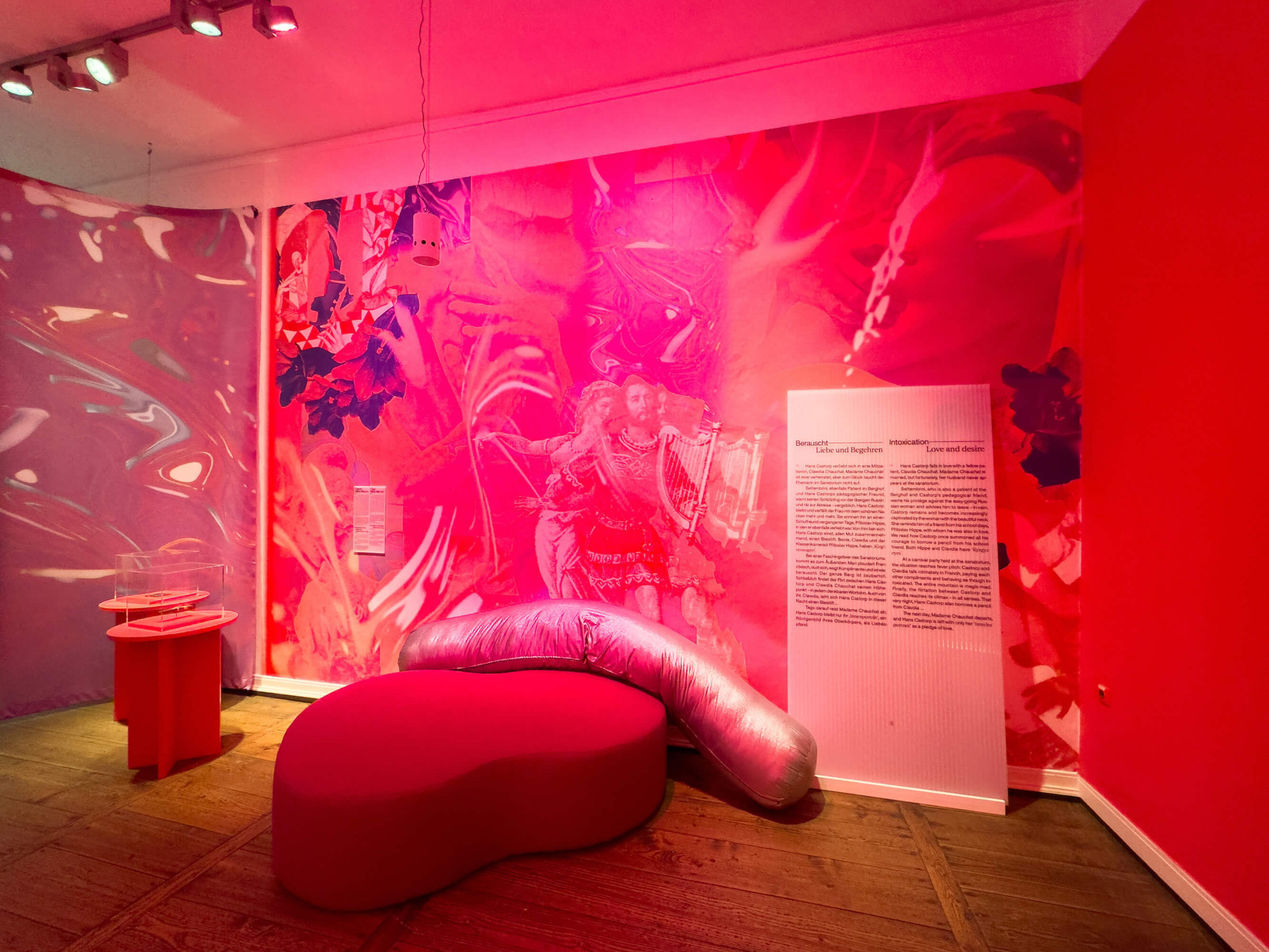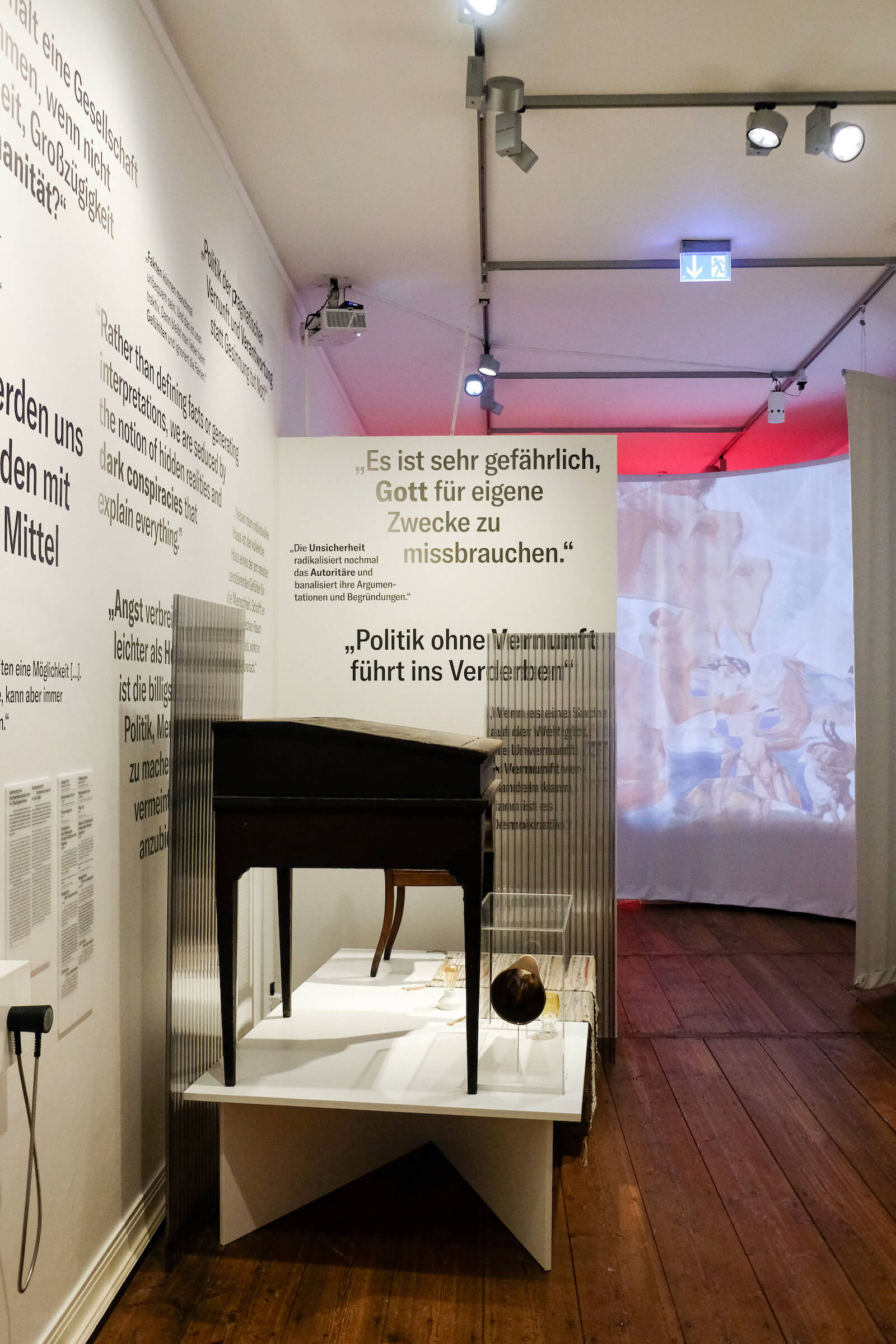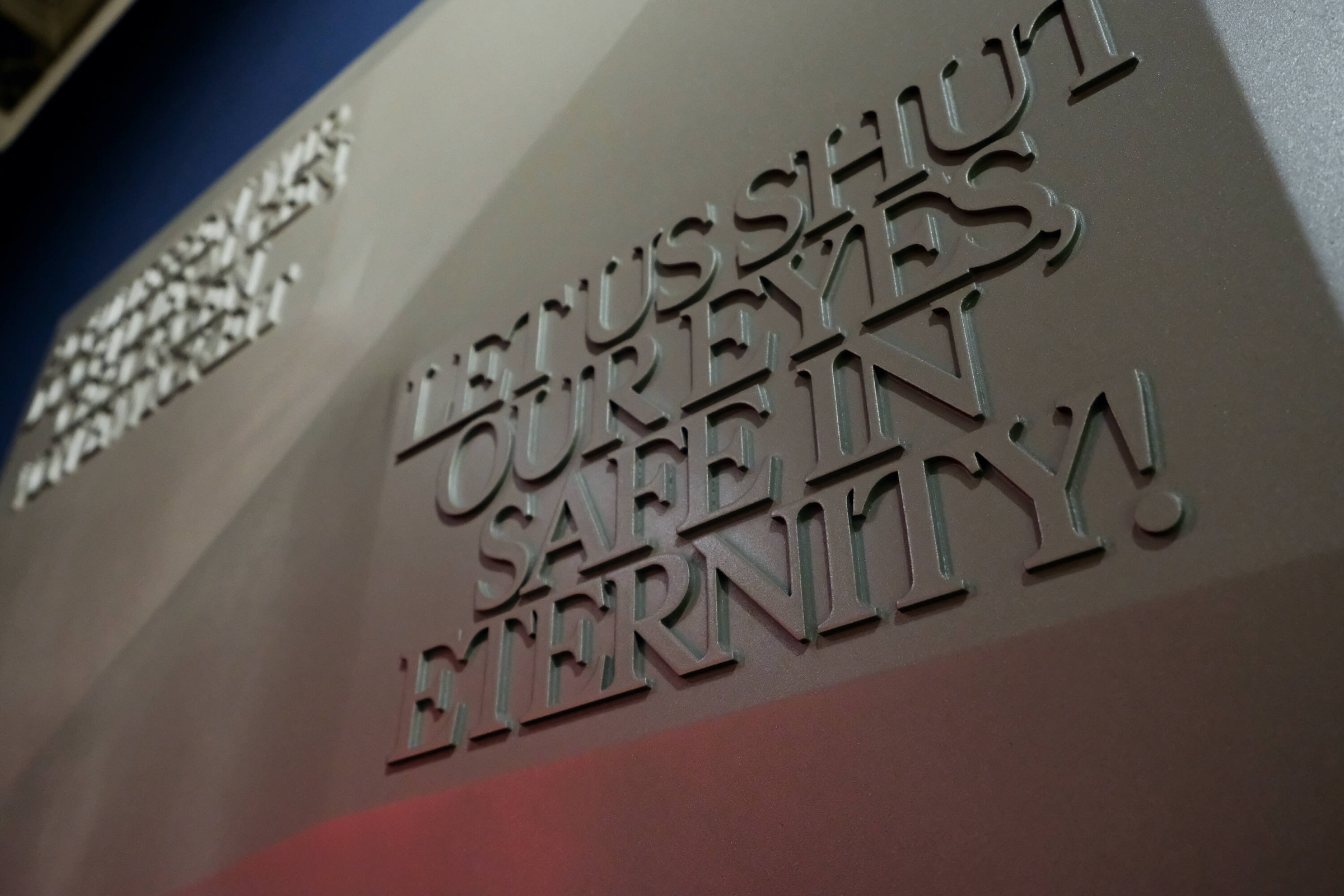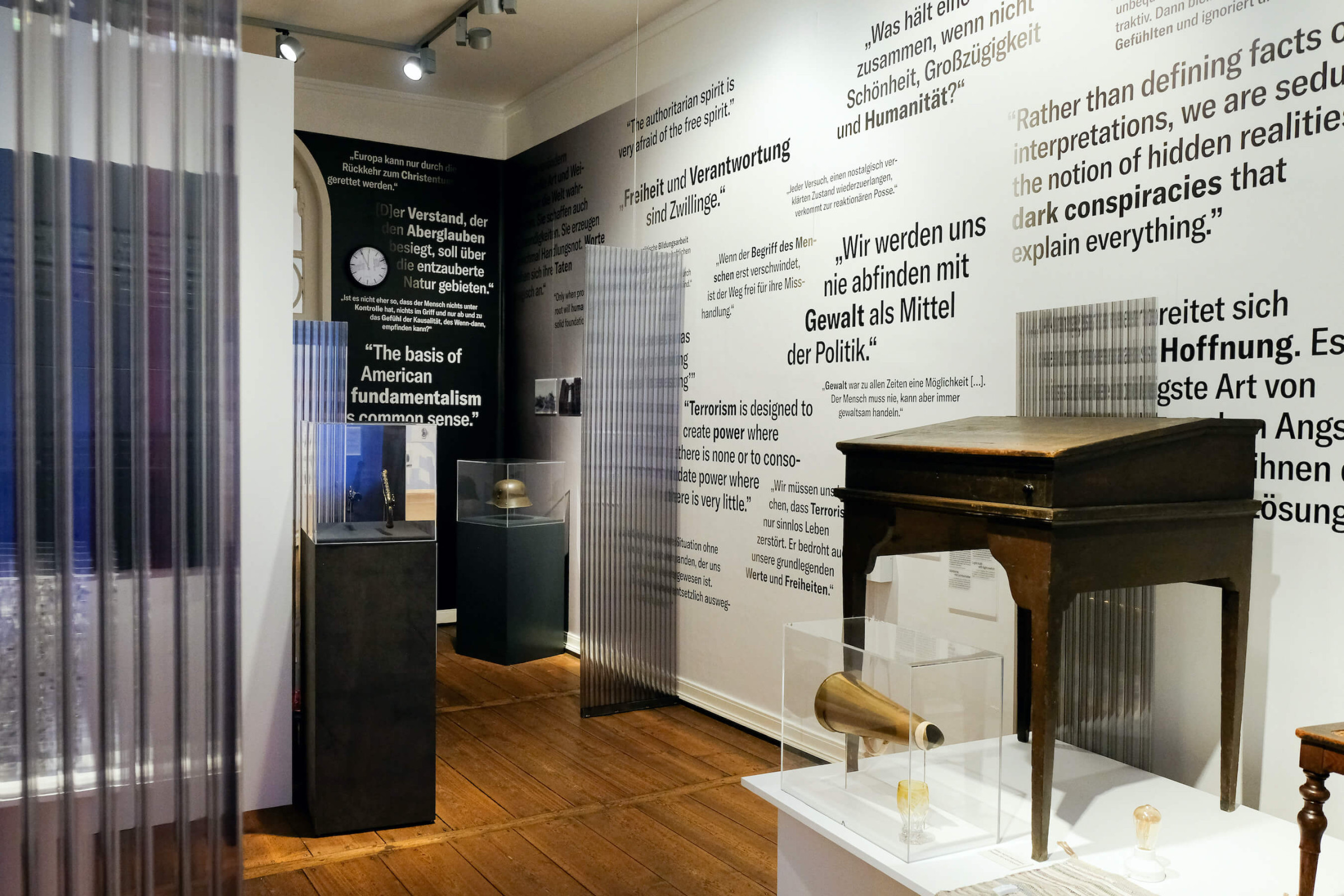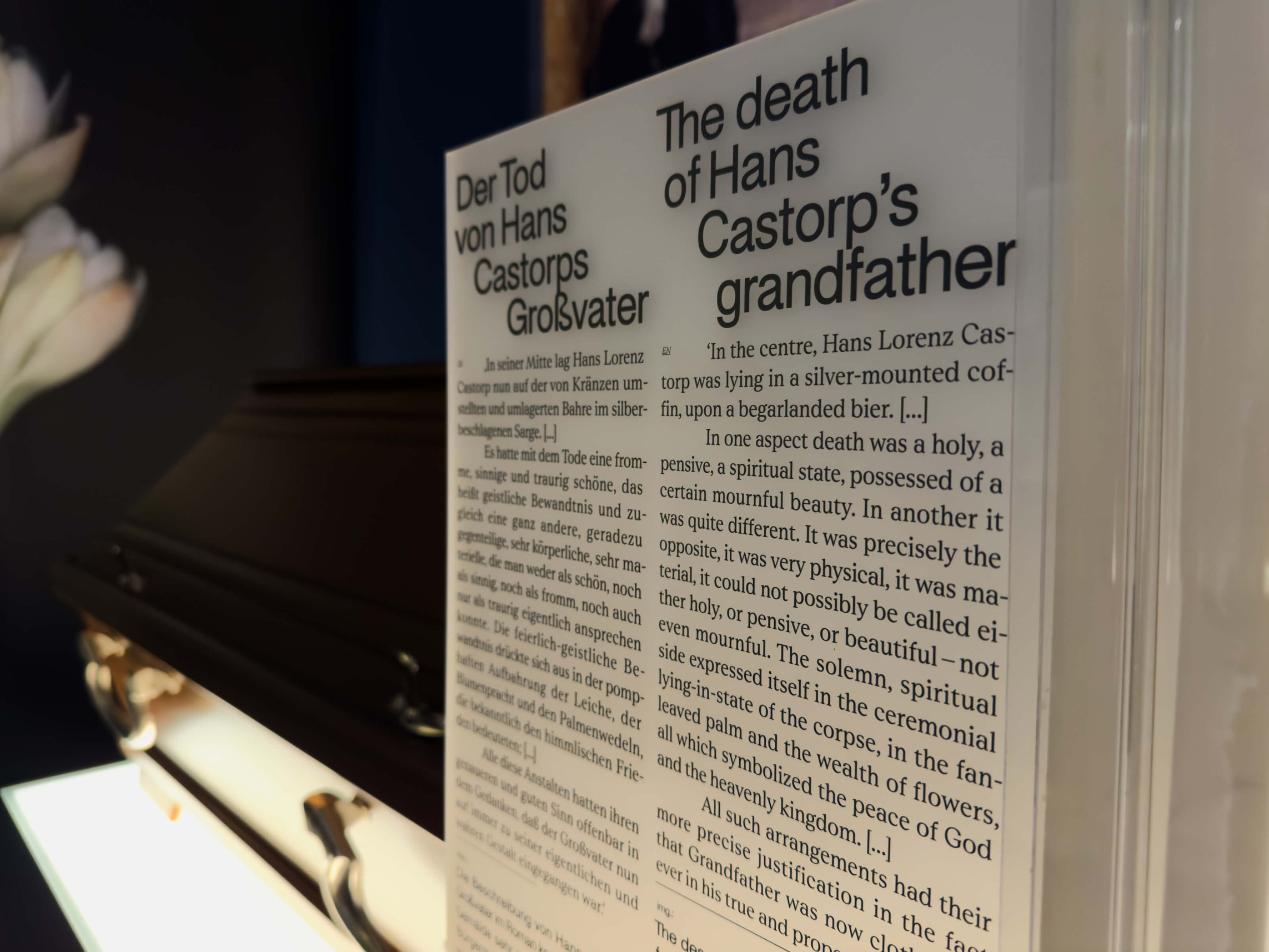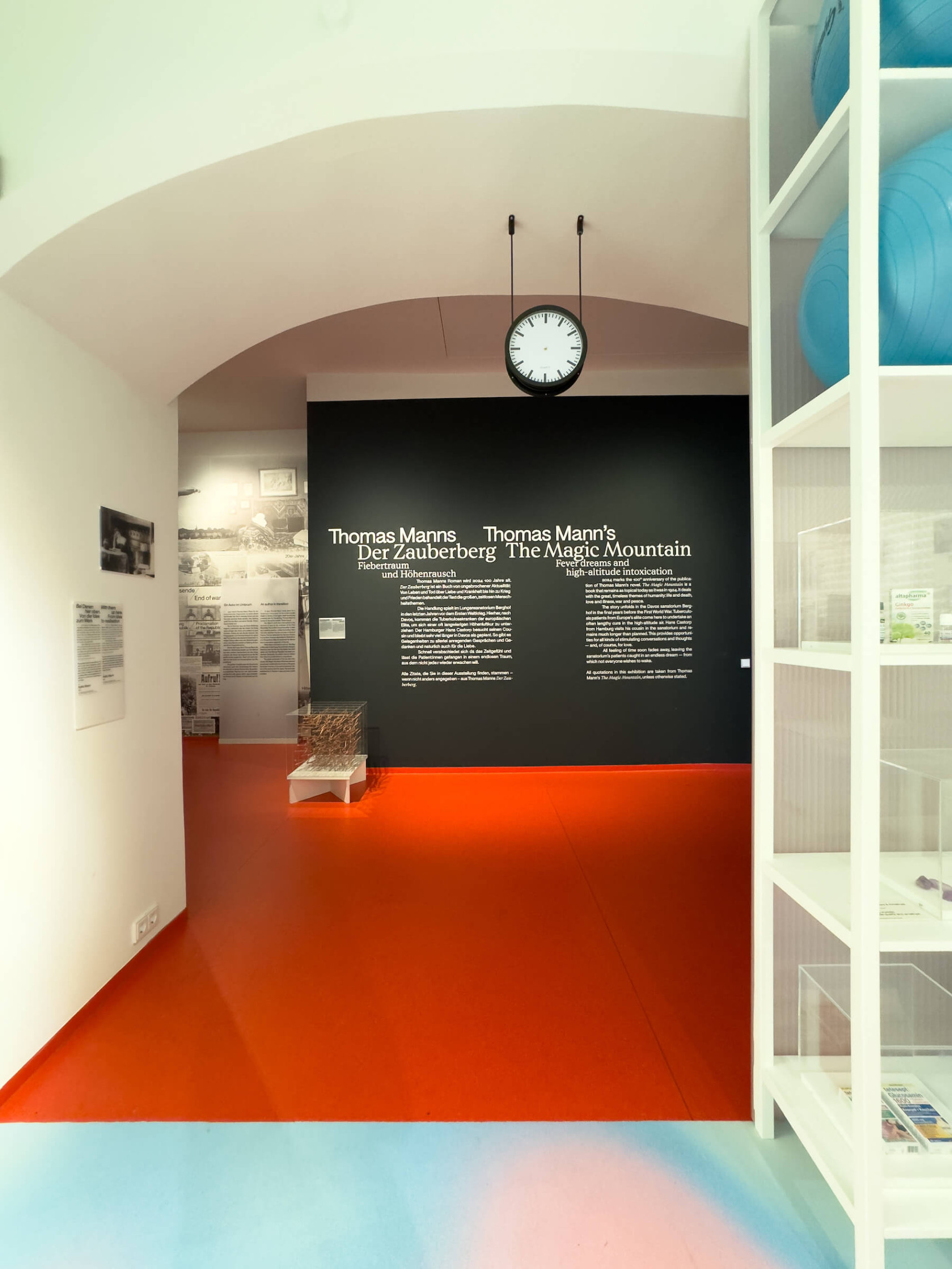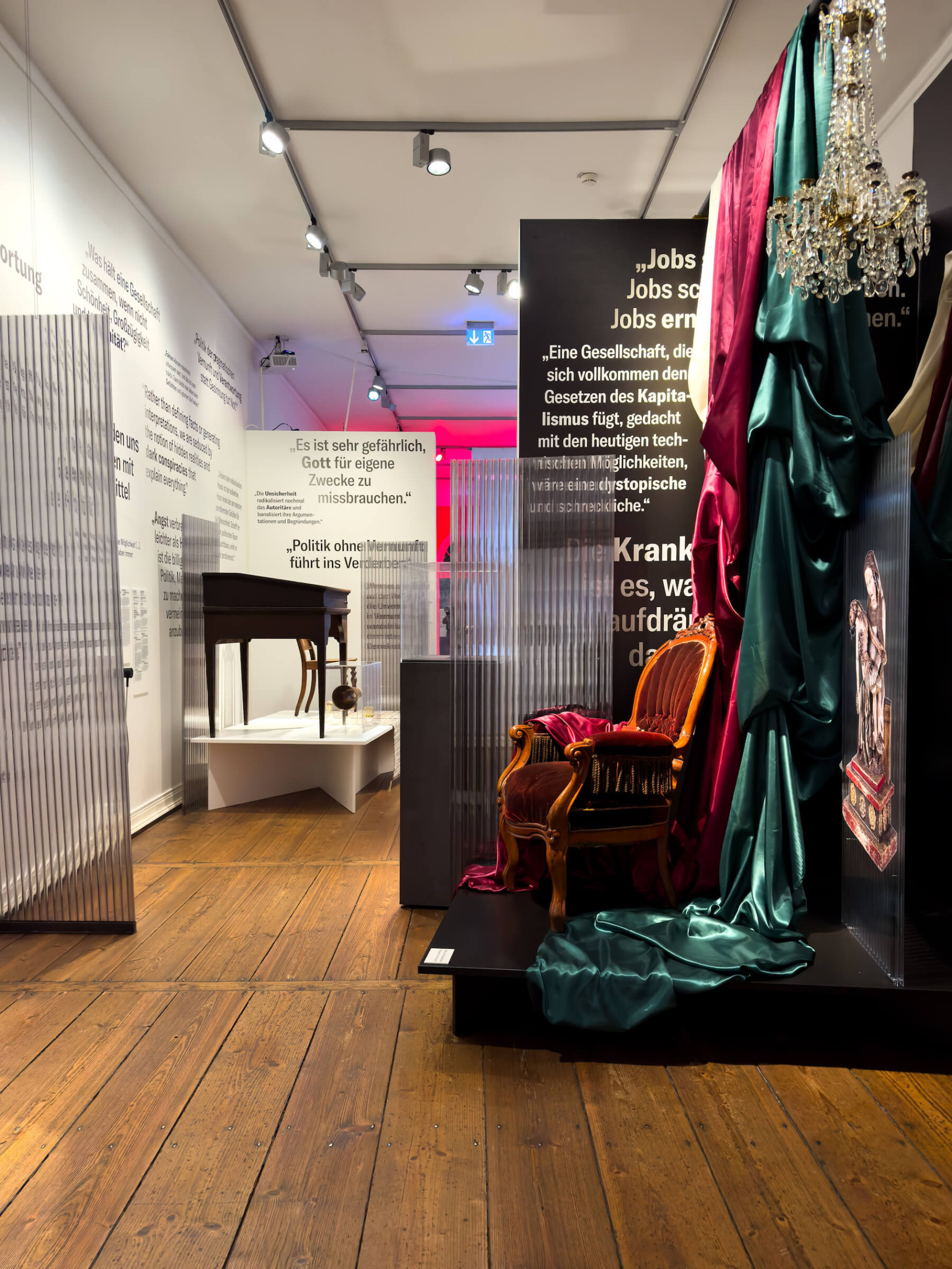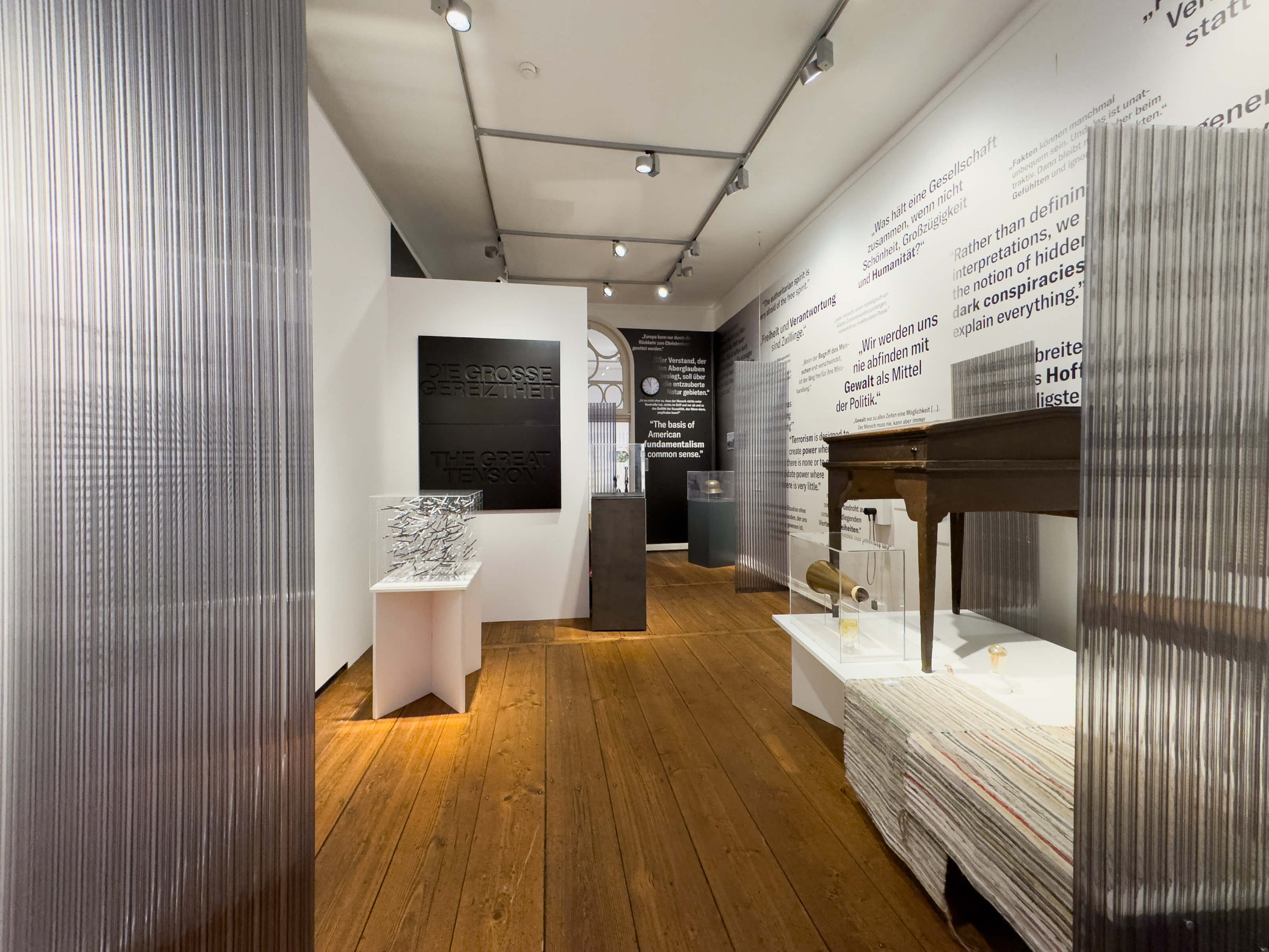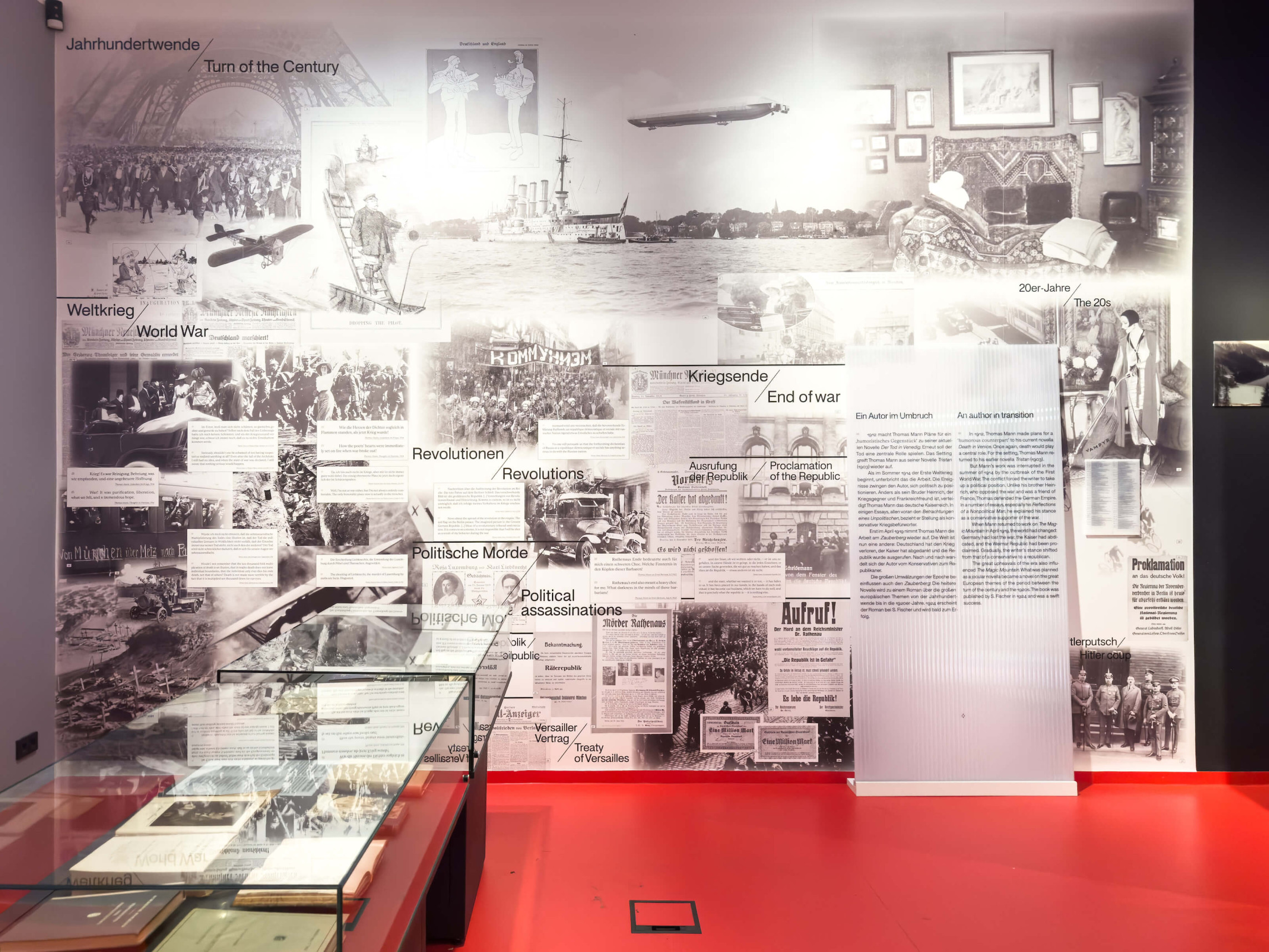
Thomas Manns — Der Zauberberg: Ausstellungsgraphik
Ausstellung
Anlässlich des 100-jährigen Jubiläums des Romans Der Zauberberg lädt die Ausstellung Thomas Manns – Der Zauberberg. Fiebertraum und Höhenrausch im St. Annen-Museum Lübeck zu einer immersiven Reise in die Welt von Thomas Mann ein. Der Roman lässt sich als ein langer Traum interpretieren, aus dem der Protagonist Hans Castorp erst im letzten Kapitel erwacht. Diese traumhafte Atmosphäre wird in sieben faszinierenden Räumen zum Leben erweckt und ermöglicht den Besucher*innen, in verschiedene Traumwelten einzutauchen.
Die Ausstellungsbeschriftungen greifen graphisch das Motiv des Auf- und Abstiegs auf, das den Zauberberg prägt. Die Überschriften sind stufenartig angeordnet und erzeugen dadurch eine dynamische visuelle Wirkung. Die Exponatstexte umfassen unterschiedliche Textarten – darunter Zitate, direkte und indirekte Rede sowie Beschreibungen der Ausstellungsstücke – die durch verschiedene Schriftarten (Default Sans & Rhetorik Serif) und Schriftstile (Italic & Regular) klar voneinander abgegrenzt werden. Die Schrifttafeln sind durch die Verwendung hochwertiger Materialien harmonisch in das Ausstellungskonzept integriert und werden so zu einem wesentlichen Teil der Inszenierung.
Besonders eindrucksvoll sind vier ausgewählte Zitate von Thomas Mann, die als dreidimensionale Texttafeln mithilfe einer CNC-Fräse umgesetzt wurden. Darüber hinaus wurden raumfüllende Wandtapeten gestaltet, die die Atmosphäre der einzelnen Ausstellungsräume prägen und intensivieren.
Schrift: Rhetorik Serif von Sascha Bente / AllCaps Type & Default Sans von Scott Vander Zee